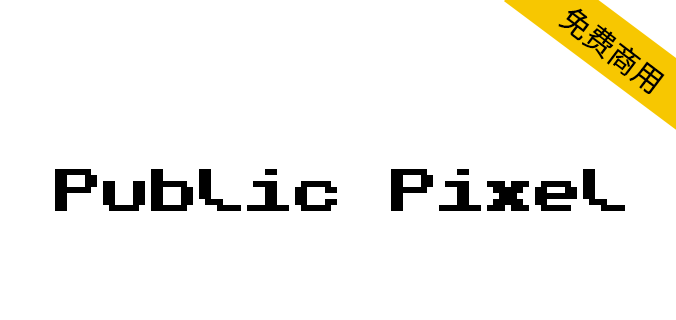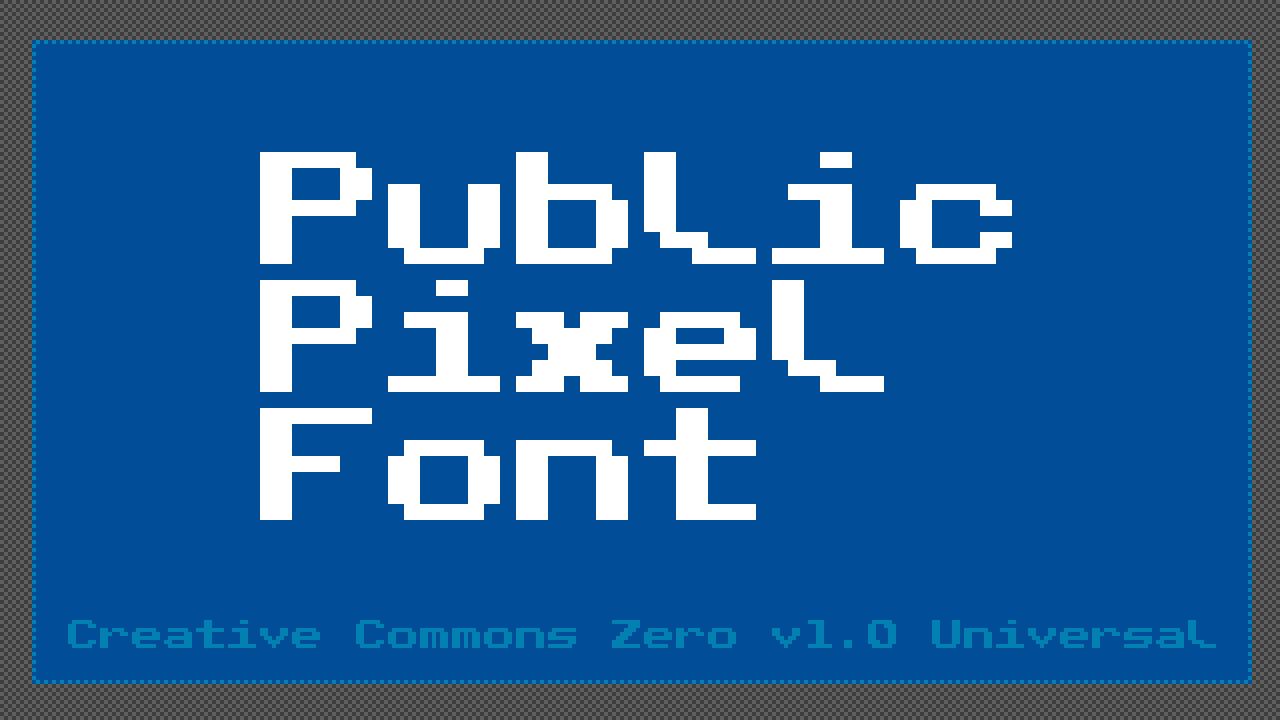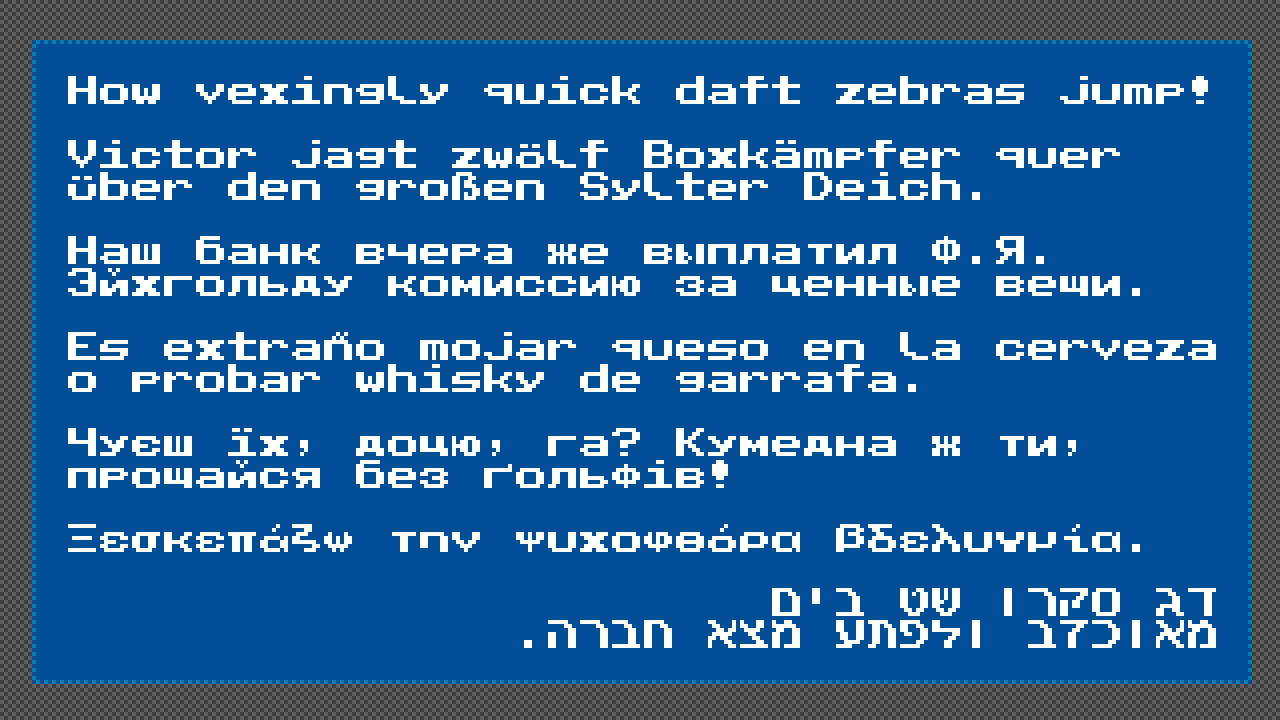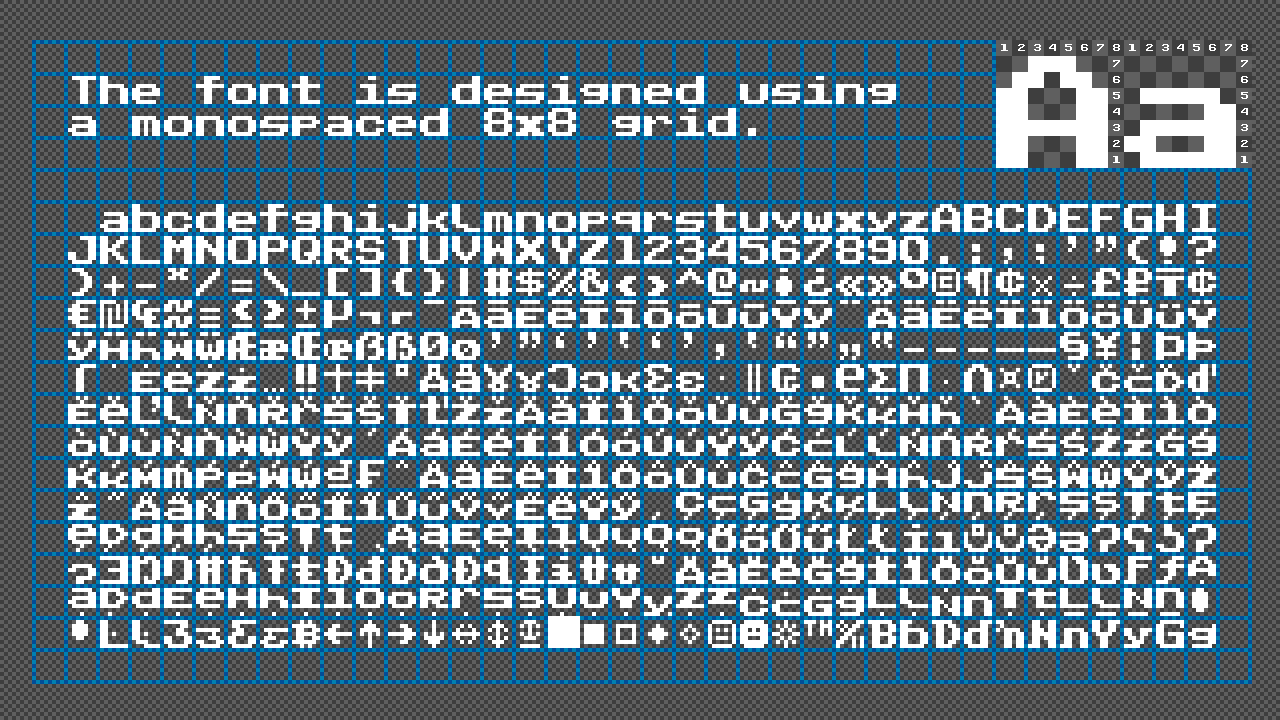
Public Pixel是一款根据CC0协议发布的免费英文字体,使用等宽的 8x8 网格设计,含 1010 个字形
推荐的字体尺寸设置:8、16、32、64、128 px(像素);6、12、24、48、96 pt(点)
支持 88 种语言(Aghem, Aja, 阿尔巴尼亚语, Aromanian, Asturian, Azeri, Basaa, Bashkir, 白俄罗斯, 布列塔尼语, 保加利亚语, 加泰罗尼亚语, Central Yambasa, Chuvash, 克罗地亚语, 捷克语, Dagbani, 丹麦语, Duala, 荷兰语, 英语, 世界语, 爱沙尼亚语, Ewe, Ewondo , 芬兰语, Fon, 法语, Fula, Gagauz, 德语, 希腊语, 希伯来语, 匈牙利语, 冰岛语, 伊博语, 印度尼西亚语, 爱尔兰语, 意大利语, Jula, Kabyle, 哈萨克语, Khoekhoe, Koyra Chiini, Koyraboro Senni, 吉尔吉斯语, Lakota, 拉丁语, 拉脱维亚语, 立陶宛语, 马赛语, 马其顿语, 马耳他语, Mapudungun, 蒙古语, Ngiemboon, Ngomba, Northern Sami, 挪威语, 波兰语, 葡萄牙语, Riffian, 罗马尼亚语, 俄语, 苏格兰盖尔语, 塞尔维亚语, 塞尔维亚语, Shawiya, Shilha, 斯洛伐克语, 斯洛文尼亚语, 西班牙语, 瑞典语、他加禄语、鞑靼语、特拉帕内克语、土耳其语、土库曼语、乌克兰语、乌兹别克语、瓦伊语、瓦尔泽德语、威尔士语、西弗里西亚语、扎尔马语、扎扎基语、祖鲁语。)